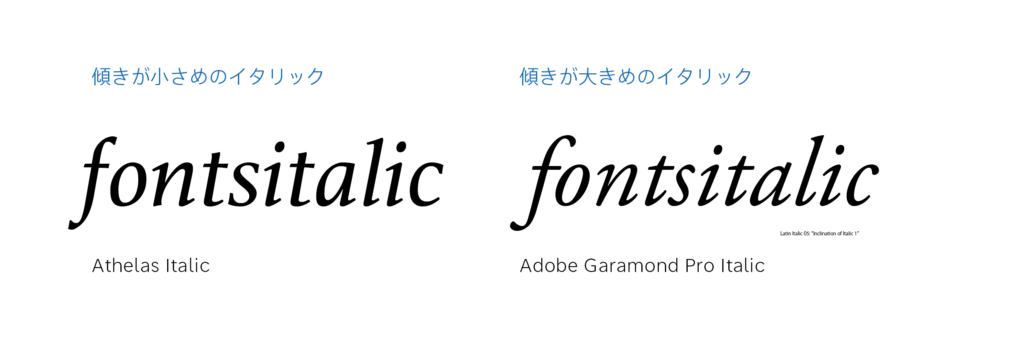
欧文イタリック05「イタリックの傾斜1」
本シリーズの前回記事「イタリックのデザインプロセス」の中でイタリックと正体の比較ポイントの一例として文字の傾斜を挙げました。傾斜の強弱は組まれた文全体の印象を左右するので、イタリックの制作やフォント選択の際に着目すべき重要な要素です。
イタリックはもともと速記用の筆記体を活字化した書体のため、傾斜角の強弱は筆記速度の強弱に関連しています。手書きで横書きの文章を書く場合、早く書こうとすればするほど文字は筆記方向である右側に傾いていく傾向があります。そのため、大きく右に傾いたデザインというのはスピード感のある動的な印象をもたらし、正体に近いほど落ち着いて静的な印象を与えることが多いと言えます。
また、傾きの強さは正体と混植されたときのイタリックの目立ち具合にも影響します。
傾きが強いと正体との字形の差が大きくなり、イタリックで組まれた部分が際立って見えてきます。
実際のイタリックの制作プロセスでも、初期の段階で角度の異なるデザインのパターンをいくつか用意し、正体との混植テストをするなどして全体の雰囲気や目立たせ方を調整することがよくあります。